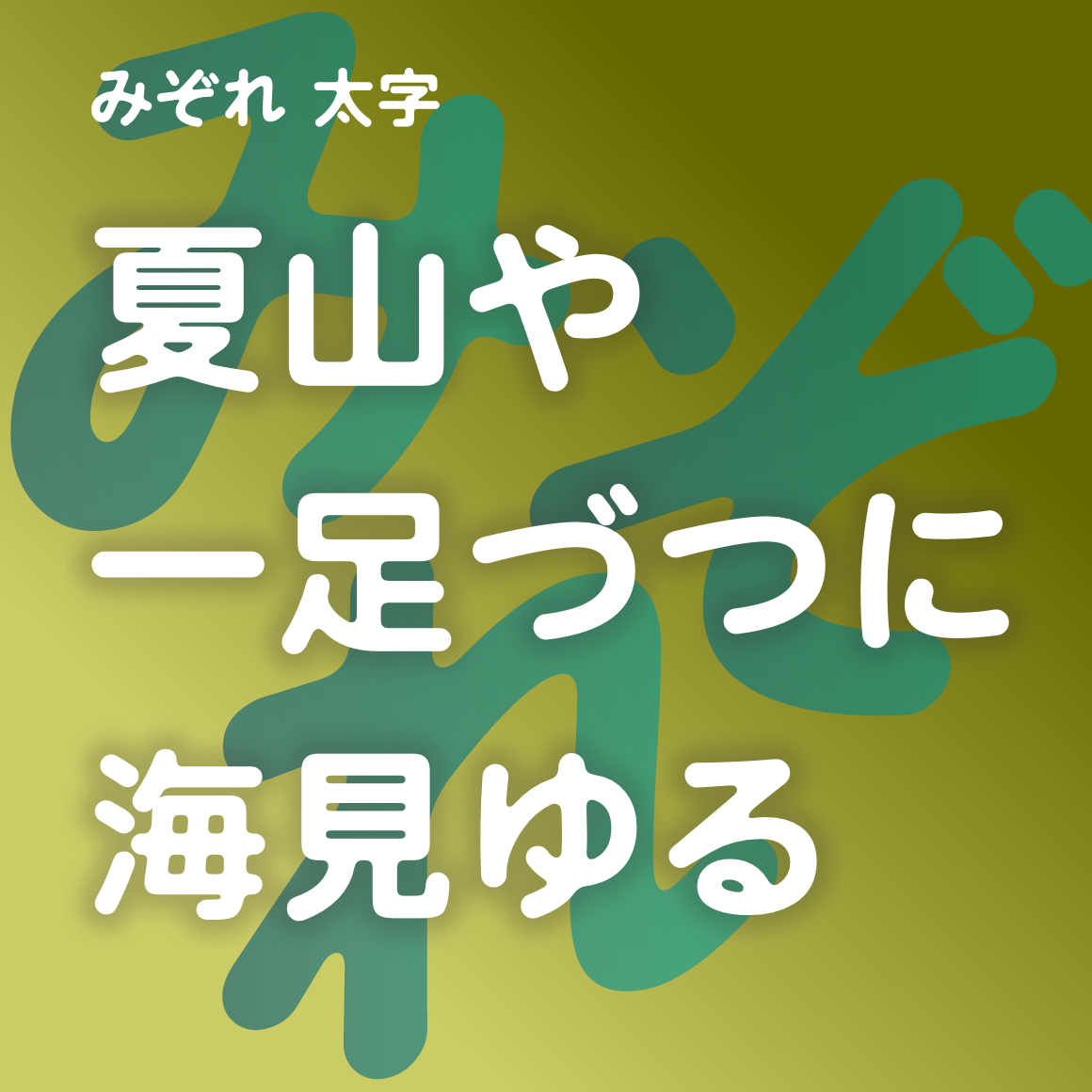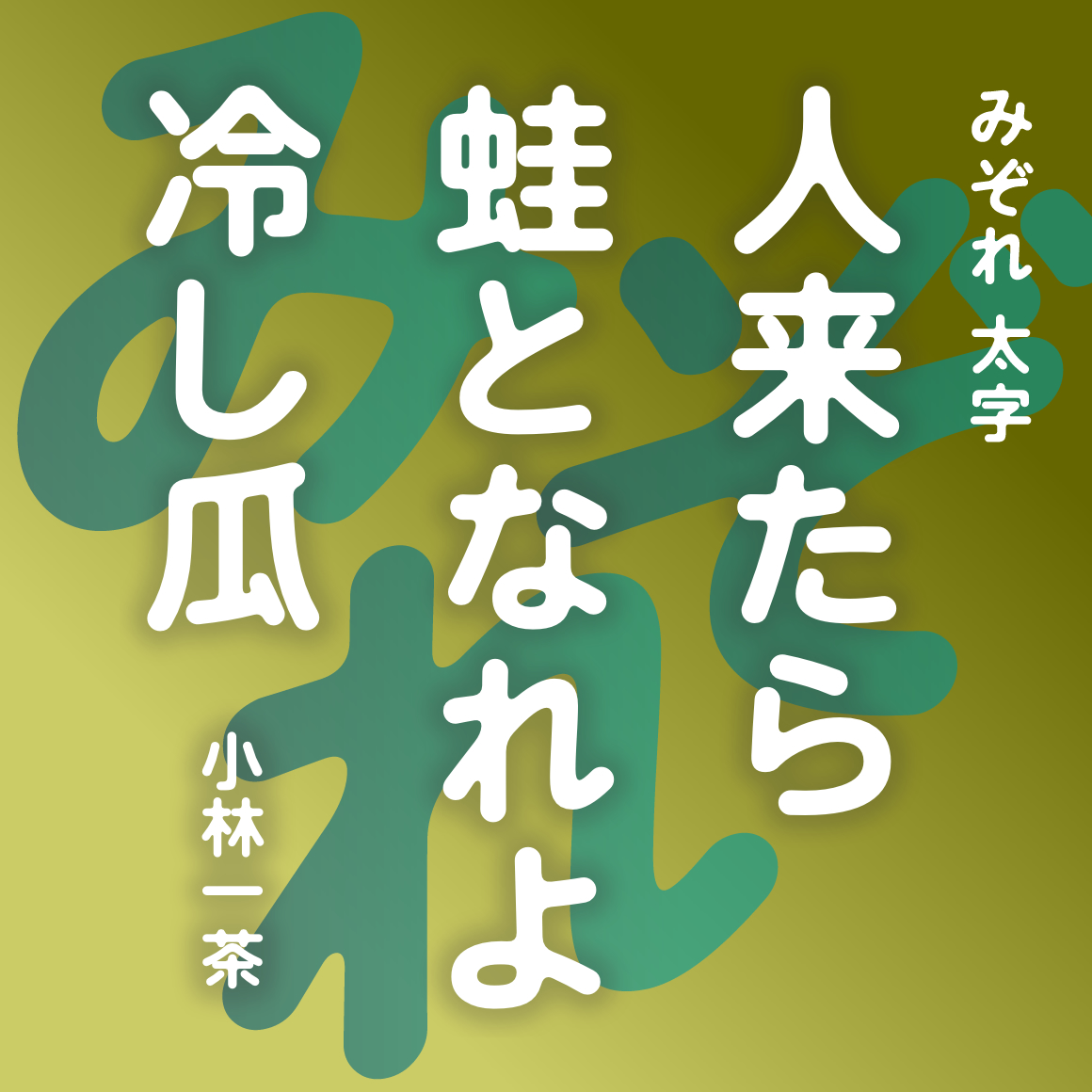
| デザイン |
線画の交点を丸くし、日本の湿潤な気候やしっとりとした感覚を、標準的な字体で表した書体…。
連想されるイメージ |
湿度・湿りけ・潤い・和み・沁みる・日本人気質・以心伝心・優しさ・こころ・曖昧・情緒・しっとり・緩い・ぬくもり・柔らかい・麗し・にじみ・とろみ・ゆったり・おぼろげ・朧・はんなり・潜在意識・サブリミナル効果・梅雨・思いやり… |